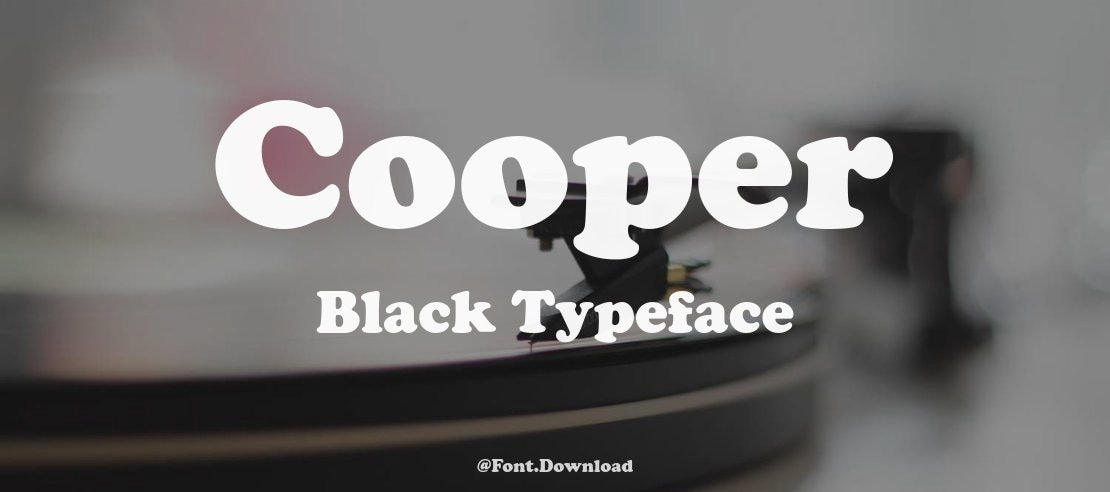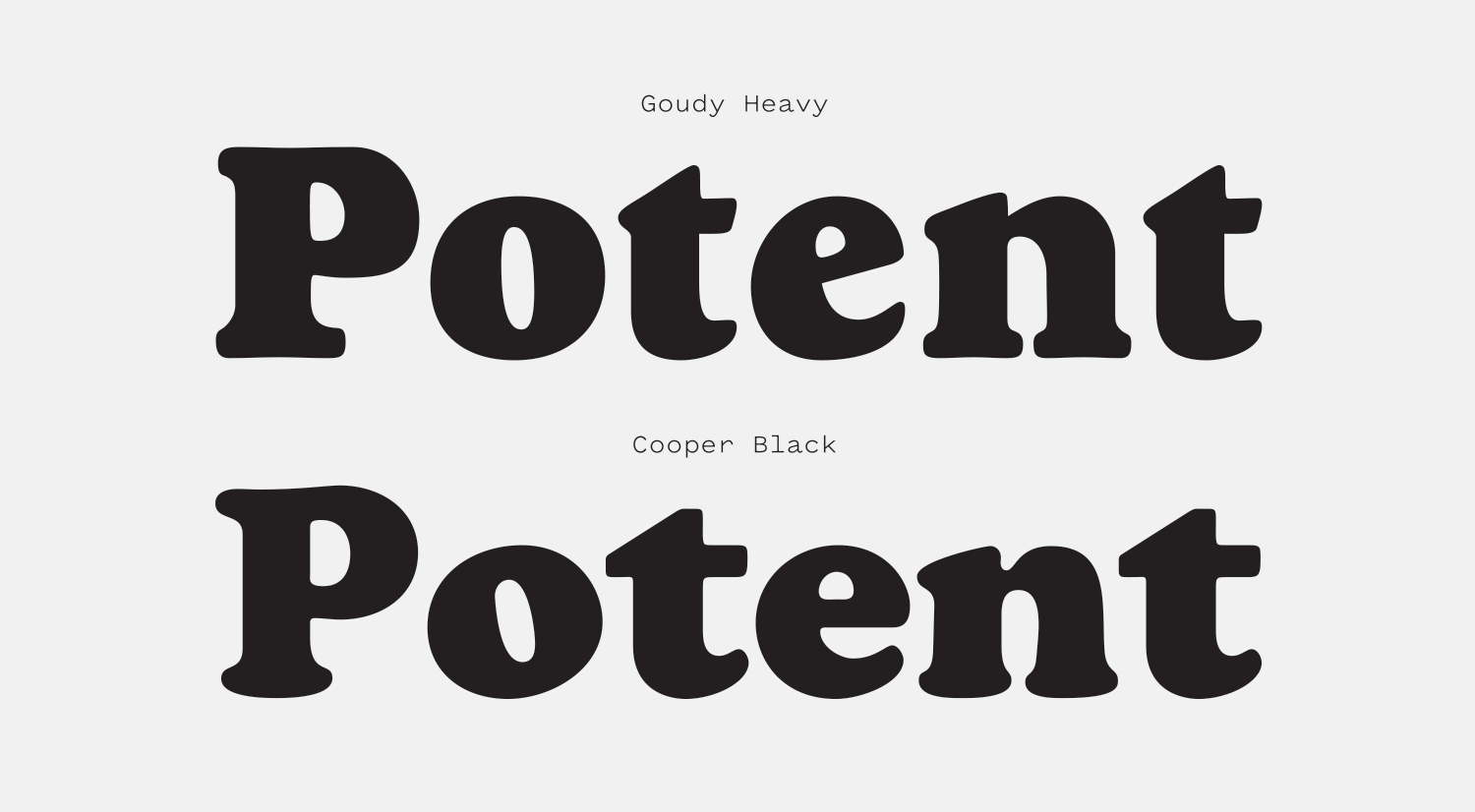
Cooper là một trong những kiểu font serif nổi bật được tạo ra bởi Oswald Bruce Cooper vào đầu thế kỷ 20. Với các đường nét tròn trịa, thân thiện nhưng vẫn giữ được độ chắc chắn, Cooper mang đến cảm giác cổ điển, đáng tin cậy và tràn đầy năng lượng – lý tưởng cho các thiết kế mang phong cách retro hoặc cần sự thu hút mạnh mẽ.
Đặc điểm nổi bật của font Cooper
• Serif bo tròn mềm mại: Không giống như các font serif truyền thống với chân chữ sắc và cứng, Cooper sử dụng các đầu chữ bo tròn tạo cảm giác thân thiện, dễ gần nhưng không kém phần ấn tượng.
• Dày và đậm: Các nét chữ của Cooper tương đối nặng, đậm, giúp font này đặc biệt hiệu quả khi sử dụng ở kích thước lớn như tiêu đề, poster hoặc logo.
• Kiểu dáng cổ điển pha hiện đại: Mặc dù là font cổ điển được phát triển từ những năm 1920, Cooper vẫn giữ được sức sống mạnh mẽ trong các thiết kế đương đại, đặc biệt là các thiết kế mang xu hướng hoài cổ.
• Dễ đọc: Dù có hình dáng nổi bật, Cooper vẫn giữ được tính dễ đọc cao. Đây là một ưu điểm lớn khi áp dụng vào các thiết kế thương mại.
Ứng dụng của font Cooper
Font Cooper có tính ứng dụng cao trong nhiều lĩnh vực nhờ sự pha trộn hài hòa giữa tính thẩm mỹ và khả năng trình bày:
• Thiết kế logo, nhãn hiệu: Được sử dụng phổ biến trong thương hiệu thời trang, đồ ăn nhanh, mỹ phẩm… Font Cooper giúp tạo điểm nhấn và truyền tải sự đáng nhớ.
• Poster, biển hiệu, tiêu đề lớn: Với độ đậm và nét đặc trưng, font Cooper đặc biệt lý tưởng cho các thiết kế cần gây ấn tượng thị giác nhanh chóng.
• Bao bì sản phẩm: Font tạo cảm giác thủ công, chất lượng cao rất hợp với các dòng sản phẩm cổ điển, handmade hoặc thiên nhiên.
• Tạp chí, bìa sách, các chiến dịch quảng cáo retro: Cooper được dùng rộng rãi trong các thiết kế theo phong cách hoài niệm hoặc vintage, nhờ tính cá tính và cảm xúc mà nó mang lại.
Font Cooper là sự kết hợp tuyệt vời giữa sự chắc chắn của serif truyền thống và sự mềm mại của các đường cong hiện đại. Với vẻ ngoài nổi bật, thân thiện và dễ sử dụng, Cooper là sự lựa chọn hoàn hảo cho những thiết kế cần sự khác biệt, cổ điển nhưng vẫn đầy tính thời đại.